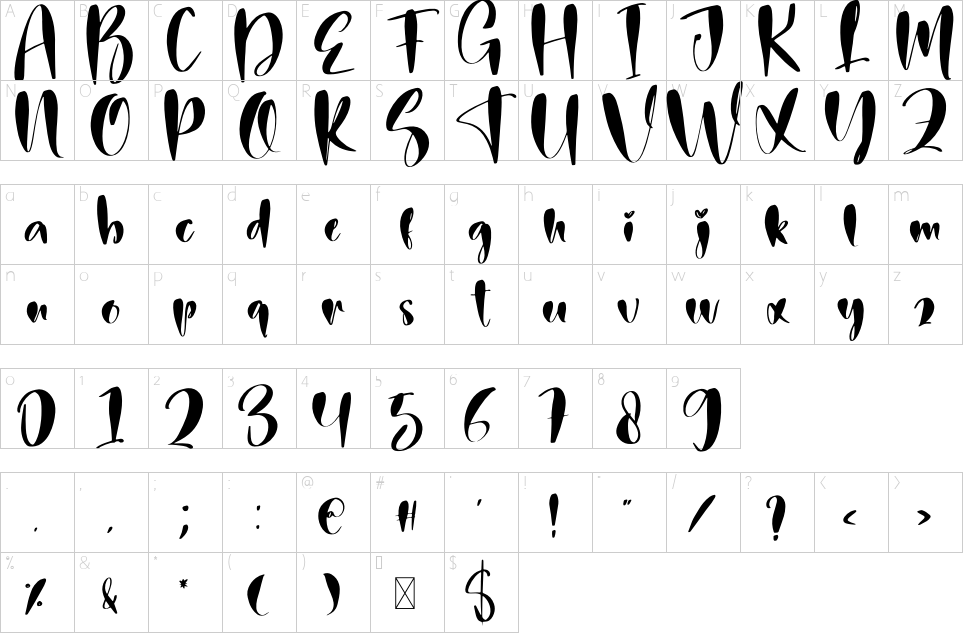
Descubra o Midday Christmas font, uma deliciosa fonte gráfica gratuita para o seu próximo projeto de design. Especialmente criada para momentos felizes como o Natal, esta fonte, desenhada por scratchones, transmite um clima de alegria e serenidade. Com seu design refinado e alegre, o Midday Christmas é perfeito para criar um toque especial em suas mensagens de Natal ou outros projetos que exigem um estilo natalino. Esta fonte foi baixada 371 vezes, o que sugere que os designers adoram o seu charme. Se você está procurando por algo leve e encantador para complementar seu trabalho de design, o Midday Christmas é um excelente escolha. Não perca essa fonte encantadora e gratuita.